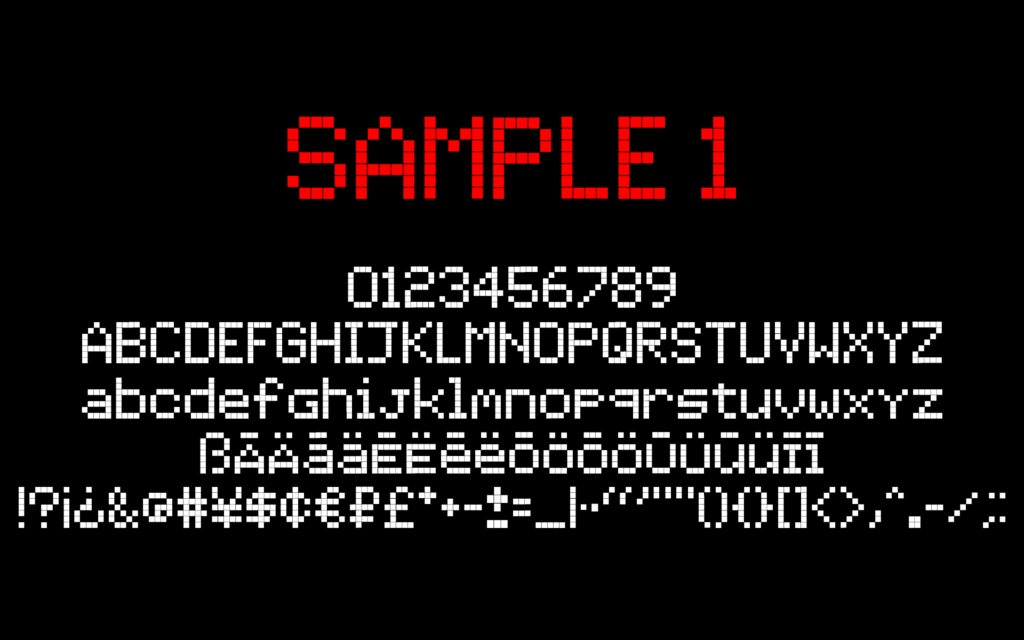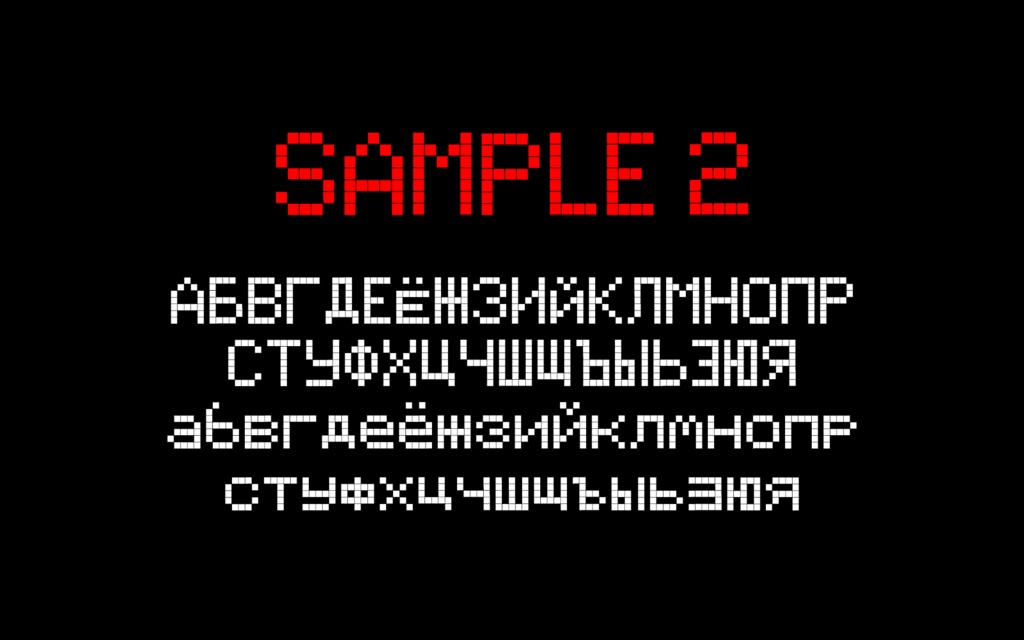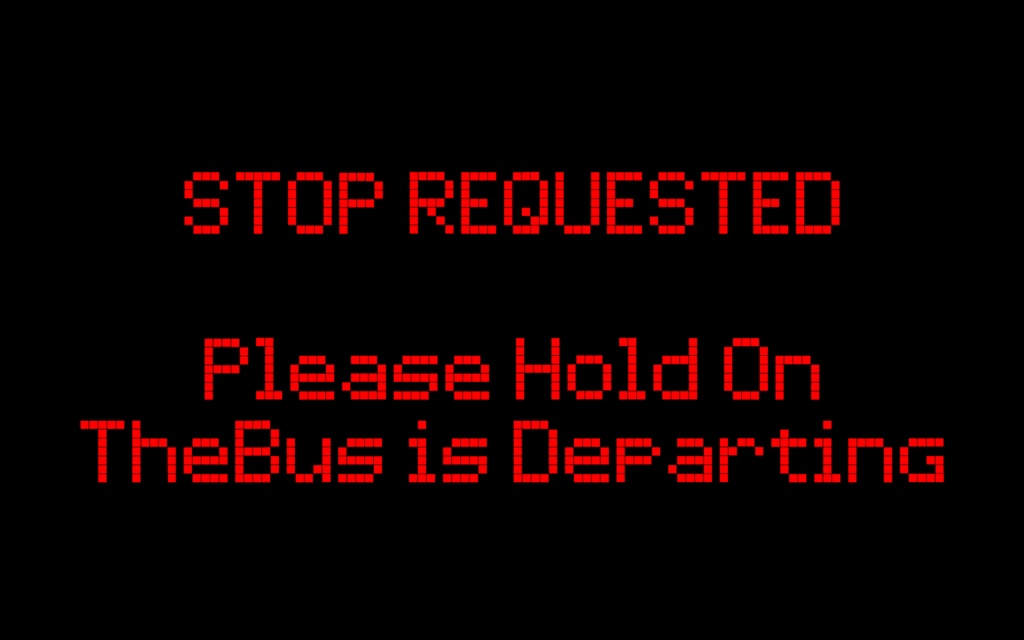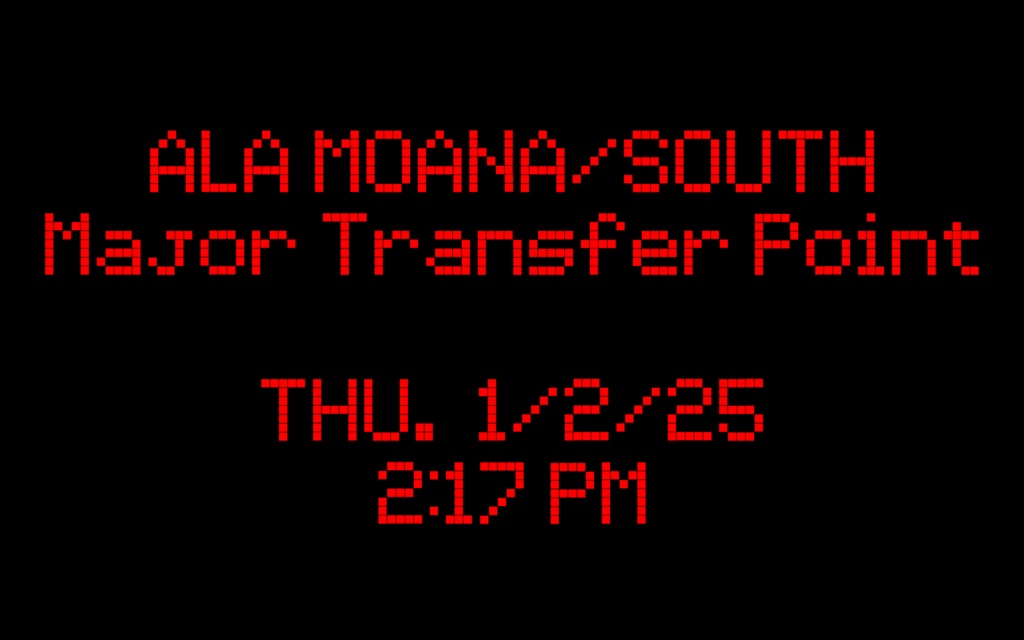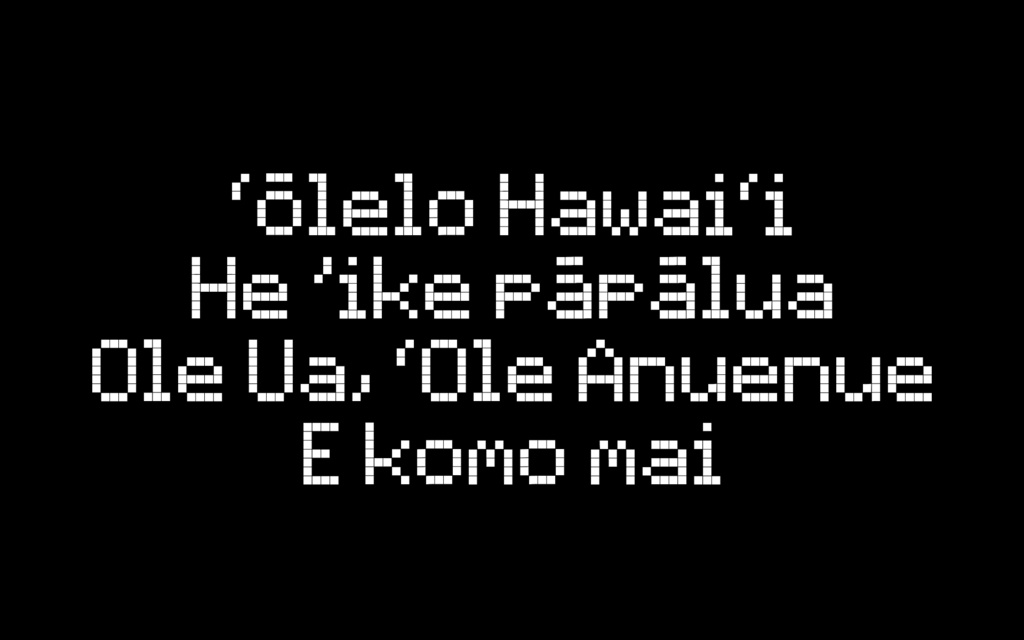
【フリーフォント】TheBus Display v2.3.1
ドットスタイルのフリーフォント、「TheBus Display v2.3.1」です。 ハワイの公共交通機関、「TheBus」の車内電光掲示板で使われているフォントを再現しています。 (無料版と支援版の内容は同一です。) 数字・アルファベット(A-Z, Ō/ō)・キリル文字・ウムラウト付文字(ÄäËëÖöÜü)・エスツェット(ß)・ハワイ語文字(ĀāĒēŌōŪūĪī)・主要な記号に対応しています。 ※ドット数の都合上、アットマーク(@)は極端に簡略化しております。また、分数など一部の複雑な記号は収録しておりません。あらかじめご了承ください。 [CHANGELOG] v2.3.1:行間がなくなっている問題を修正し、アットマーク(@)を追加しました。